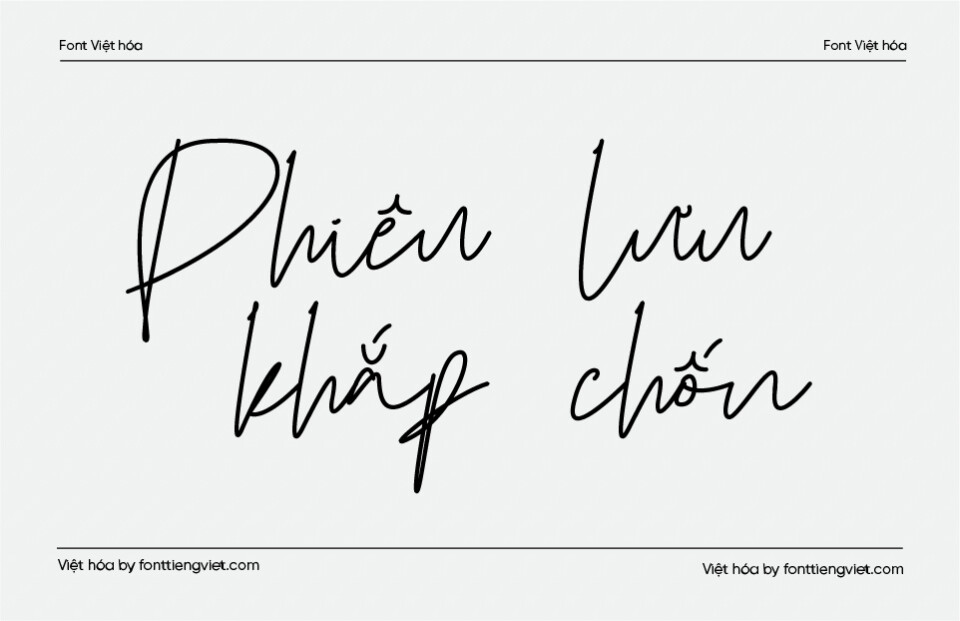
Font Việt hóa 1FTV VIP Kalmost – Chữ Ký Viết Tay Tinh Tế Cho Thiệp Cưới & Thiệp Mời
Trong thế giới thiết kế đồ họa hiện đại, việc lựa chọn một bộ Font Miễn Phí chất lượng luôn là ưu tiên hàng đầu của các nhà sáng tạo. Đặc biệt đối với các ấn phẩm mang tính cá nhân hóa cao như thiệp cưới hay thư mời sự kiện, Font Việt hóa 1FTV VIP Kalmost – Chữ Ký Viết Tay Tinh Tế Cho Thiệp Cưới & Thiệp Mời đã khẳng định được vị thế riêng biệt nhờ đường nét uyển chuyển và phong cách sang trọng. Bộ font này không chỉ đơn thuần là những ký tự số hóa mà còn chứa đựng cái hồn của nghệ thuật viết tay thủ công, mang đến cảm giác gần gũi nhưng không kém phần đẳng cấp cho mọi bản thiết kế tại Việt Nam.
Đặc điểm nổi bật của Font Việt hóa 1FTV VIP Kalmost – Chữ Ký Viết Tay Tinh Tế Cho Thiệp Cưới & Thiệp Mời
Font Việt hóa 1FTV VIP Kalmost nổi bật với cấu trúc các nét nối mềm mại, mô phỏng hoàn hảo thao tác đưa bút của một nghệ nhân viết chữ đẹp. Điểm mạnh lớn nhất chính là sự cân bằng giữa tính nghệ thuật và khả năng đọc hiểu. Dù sở hữu nhiều chi tiết uốn lượn phức tạp, các con chữ vẫn giữ được độ rõ nét cần thiết trên nhiều bề mặt in ấn khác nhau.
Phong cách thiết kế chữ ký độc bản
Được thiết kế dựa trên cảm hứng từ những dòng chữ ký tay bay bổng, 1FTV VIP Kalmost tạo ra một không gian thẩm mỹ đầy lãng mạn. Các ký tự hoa được chăm chút tỉ mỉ với độ nghiêng tự nhiên, tạo nên điểm nhấn mạnh mẽ cho tiêu đề thiệp mời hoặc tên cô dâu chú rể. Sự tinh tế này giúp người xem cảm nhận được sự trân trọng và tâm huyết mà người gửi đặt vào từng tấm thiệp.
Tối ưu hóa tiếng Việt hoàn chỉnh
Khác với các bộ phông chữ nước ngoài thường gặp lỗi dấu khi gõ tiếng Việt, phiên bản Việt hóa này đã được căn chỉnh kỹ lưỡng. Các dấu thanh như huyền, sắc, hỏi, ngã, nặng được đặt ở vị trí thẩm mỹ nhất, không làm phá vỡ cấu trúc tổng thể của từ. Điều này đặc biệt quan trọng trong giáo dục và thiết kế chuyên nghiệp, giúp thông điệp truyền tải chính xác và đẹp mắt.
Ứng dụng thực tế của Font Việt hóa 1FTV VIP Kalmost trong đời sống
Không chỉ giới hạn trong lĩnh vực cưới hỏi, bộ font này còn có tính ứng dụng cực kỳ đa dạng trong nhiều dự án sáng tạo khác nhau, từ thương hiệu cá nhân đến trang trí không gian học đường.
Thiết kế thiệp cưới và thư mời sự kiện
Đây chính là “mảnh đất” dụng võ chính của Font Việt hóa 1FTV VIP Kalmost – Chữ Ký Viết Tay Tinh Tế Cho Thiệp Cưới & Thiệp Mời. Khi kết hợp với các tông màu pastel hoặc ép kim vàng, bộ chữ sẽ tạo nên một tổng thể vô cùng quý phái. Nó giúp biến những tấm thiệp mời thông thường thành một tác phẩm nghệ thuật lưu niệm đáng giá.
Sáng tạo nội dung số và bao bì sản phẩm
Nhiều blogger và chủ cửa hàng handmade lựa chọn font chữ này để làm watermark (hình mờ) hoặc thiết kế logo theo dạng chữ ký. Sự thanh mảnh của các nét chữ giúp hình ảnh thương hiệu trở nên nhẹ nhàng và dễ đi vào lòng người hơn. Trong giáo dục, giáo viên có thể dùng font này để làm tiêu đề bài giảng hoặc giấy khen để tạo sự khác biệt và khích lệ học sinh.
Để phát huy tối đa vẻ đẹp của Font Việt hóa 1FTV VIP Kalmost, người dùng nên lưu ý một số kỹ thuật nhỏ khi dàn trang. Việc kết hợp font chữ ký này với các font chữ không chân (Sans-serif) đơn giản sẽ giúp tạo ra sự tương phản tuyệt vời, làm nổi bật những thông tin quan trọng nhất trên bản thiết kế.
Lưu ý về khoảng cách và kích thước
Vì đây là dạng font script (viết tay), việc để kích thước quá nhỏ có thể gây khó đọc. Hãy đảm bảo cỡ chữ đủ lớn để các nét thanh nét đậm được hiển thị rõ ràng. Ngoài ra, không nên viết hoa toàn bộ các từ bằng font này vì sẽ làm mất đi tính liên kết tự nhiên của các nét nối.